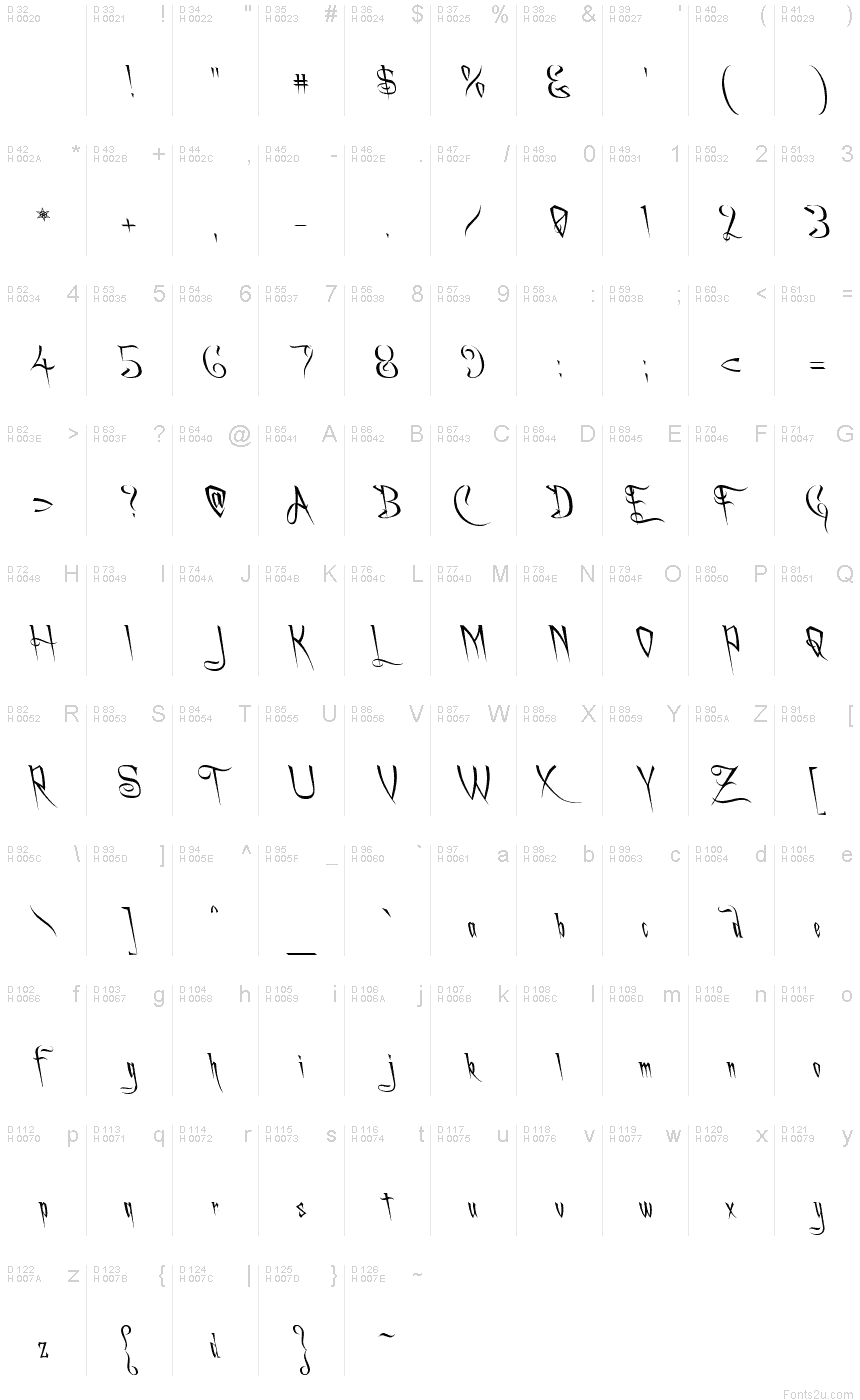
A Charming Font Leftleaning
A Charming Font Leftleaning di GeM / A. Höfeld è un carattere gotico gratuito che reinterpreta la calligrafia classica in una chiave più oscura e drammatica. Le lettere si protendono verso sinistra con un'inclinazione tagliente, quasi come inchiostro catturato nel gesto, con tratti lunghi e curve appuntite che risultano eleganti e un po' sinistre. La famiglia A Charming Font Leftleaning conferisce un'atmosfera suggestiva, quasi fiabesca: romantica, ma con del mordente.
Con A Charming Font Leftleaning, i tuoi titoli sembreranno presi direttamente da manoscritti maledetti, mappe fantasy, poster di band o fanzine occulte. Questo font gratuito è perfetto anche per inviti di nozze in stile gotico, loghi di giochi e merchandising ispirato al mondo dei tatuaggi, dove cerchi un impatto immediato. Usalo in grande formato, dagli spazio per respirare e abbinalo a un sans serif pulito e sobrio per il testo principale, così da far risaltare il suo carattere grafico.